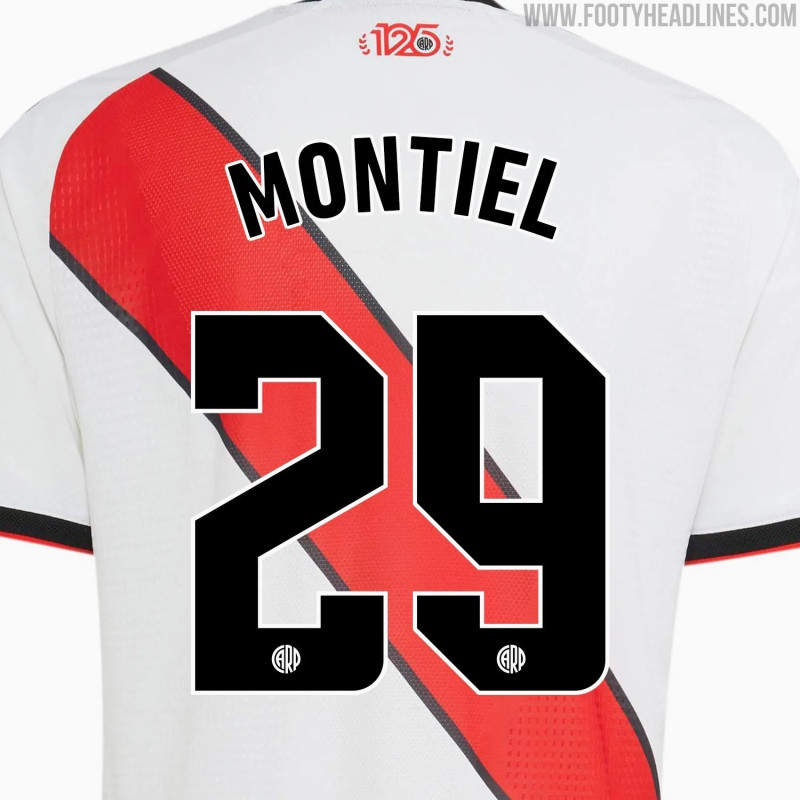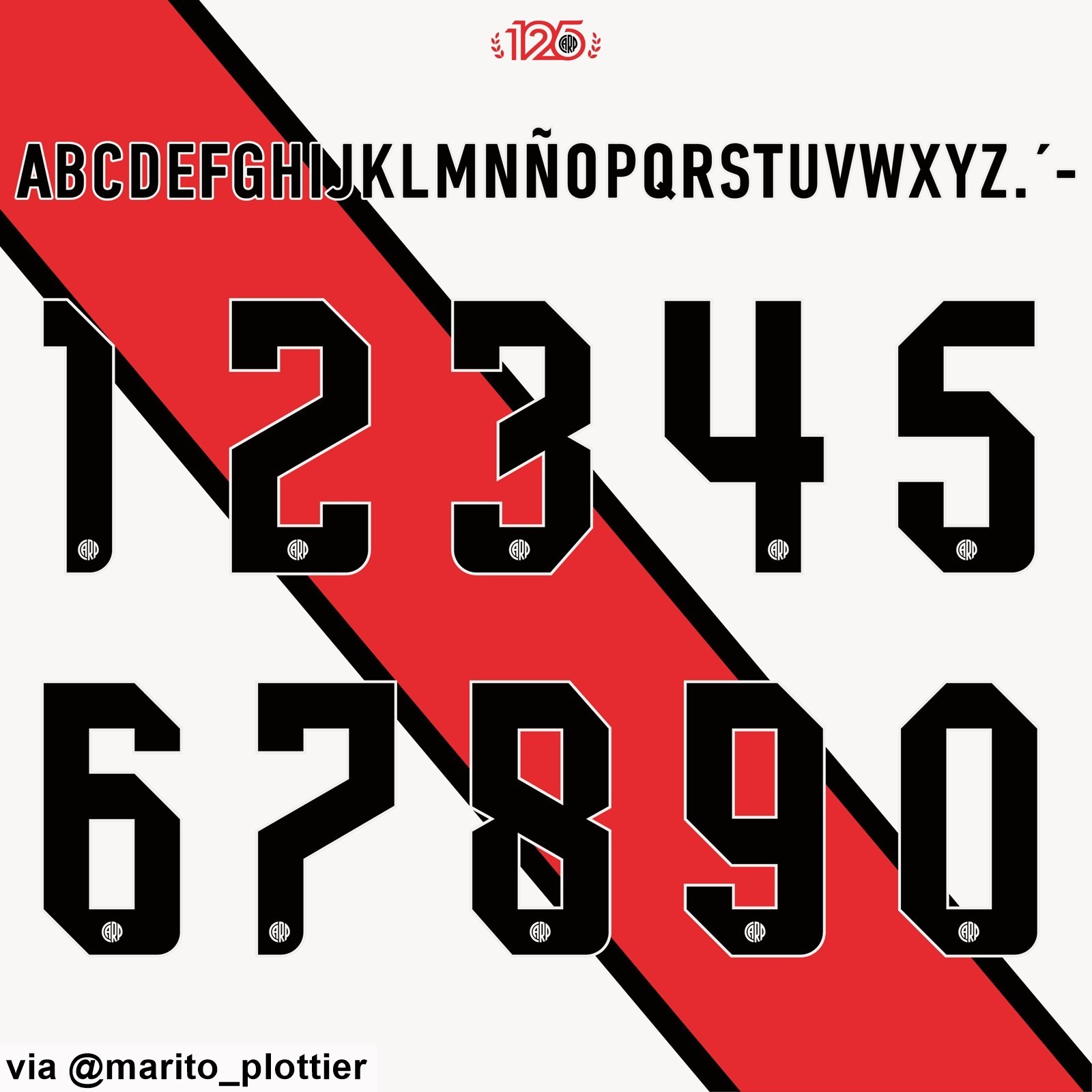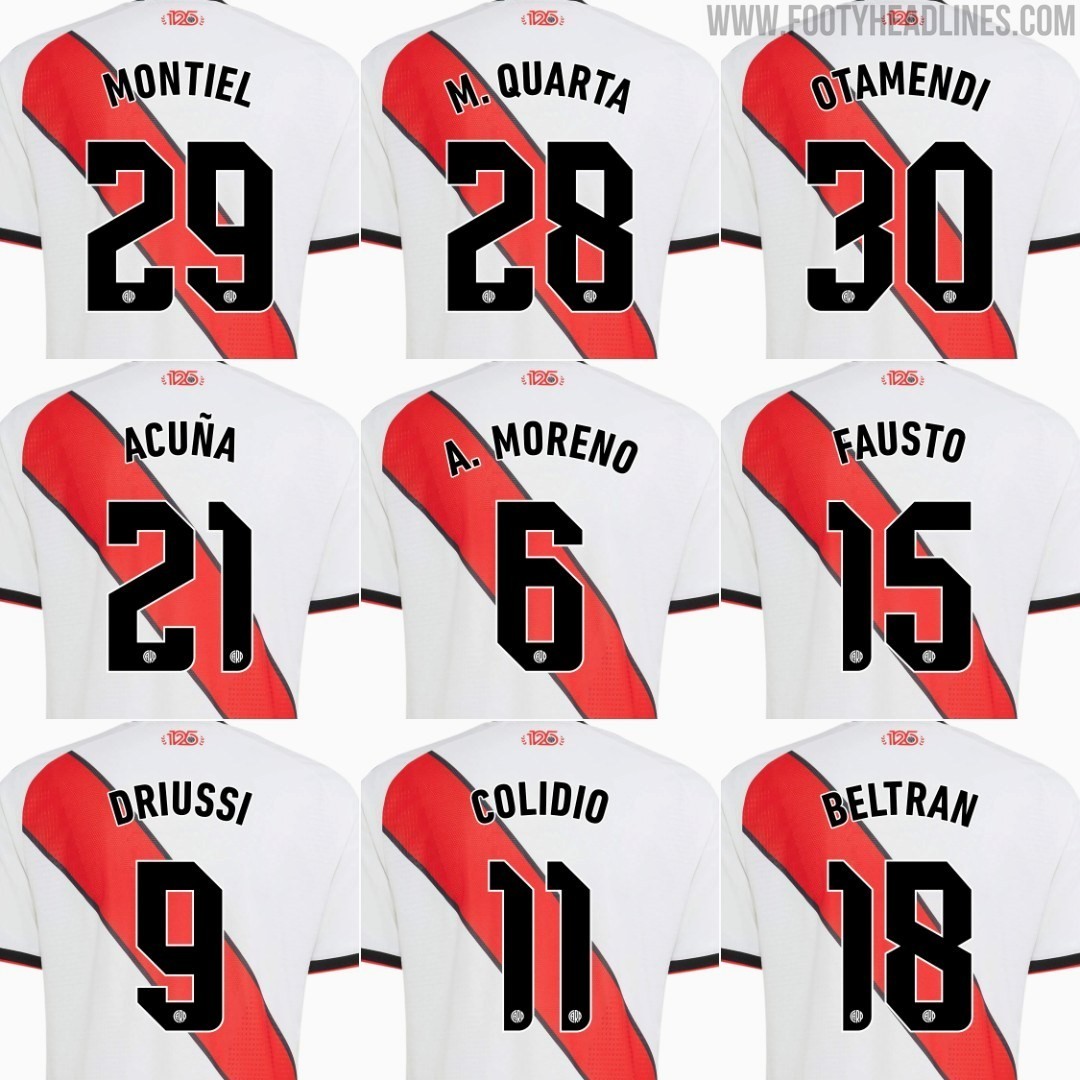
Rilasciato il nuovissimo font della maglia del River Plate 26-27
- Lancio Ufficiale: Il River Plate ha presentato ufficialmente un font tutto nuovo per le maglie della stagione 2026-2027, dopo il lancio della nuova maglia da casa.
- Caratteristiche del Design: Il nuovo font è più nitido e spigoloso, con numeri neri a tinta unita e un sottile bordo bianco per garantire leggibilità, e include il classico stemma “CARP” in fondo a ogni numero.
Dopo il lancio della nuova maglia da casa, il River Plate ha presentato ufficialmente un font tutto nuovo per le maglie della stagione 2026-2027.
Presentata la prima maglia del River Plate 26-27
Carattere tipografico della prima maglia del River Plate 26-27
La nuova maglia del River Plate 26-27 introduce un aggiornamento evidente, con un design più nitido e decisamente più spigoloso rispetto alla tipografia usata nella precedente stagione 2025-26.
Le lettere e i numeri presentano tagli spigolosi e decisi che conferiscono alla tipografia un aspetto moderno e aggressivo. I numeri hanno una base nera a tinta unita con un sottile bordo bianco, che garantisce una perfetta leggibilità sullo sfondo della iconica fascia rossa del club.
Come da tradizione, il classico stemma con il monogramma “CARP” del River Plate è posizionato in fondo a ogni numero.